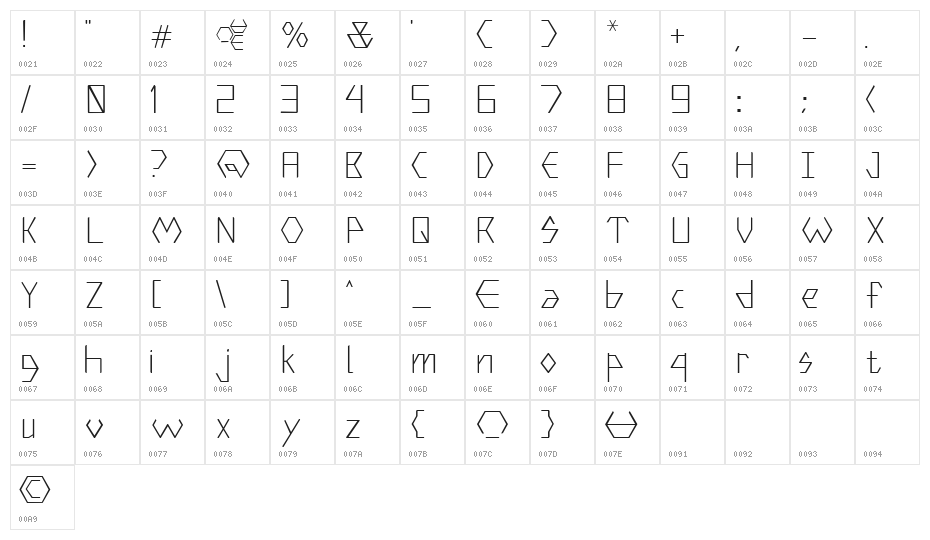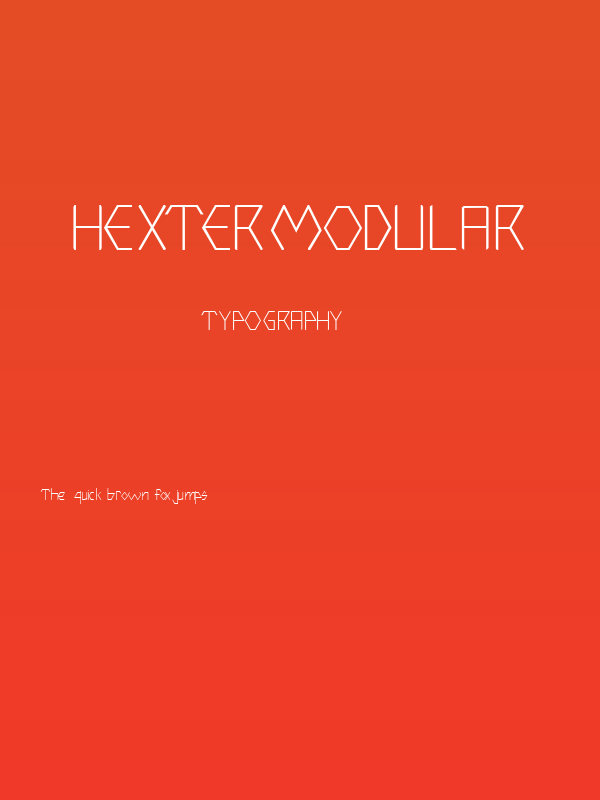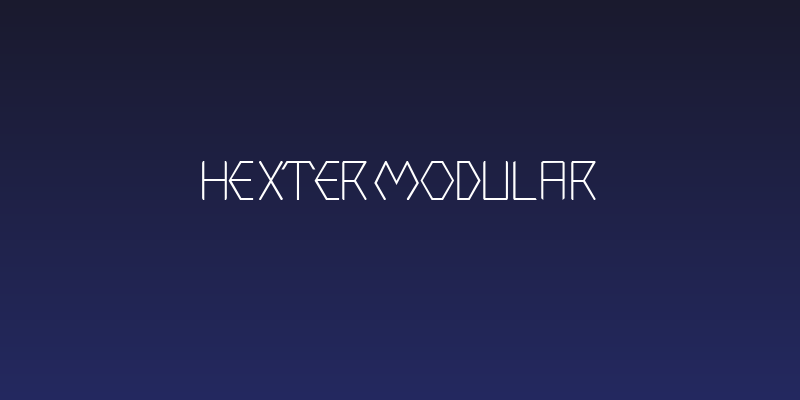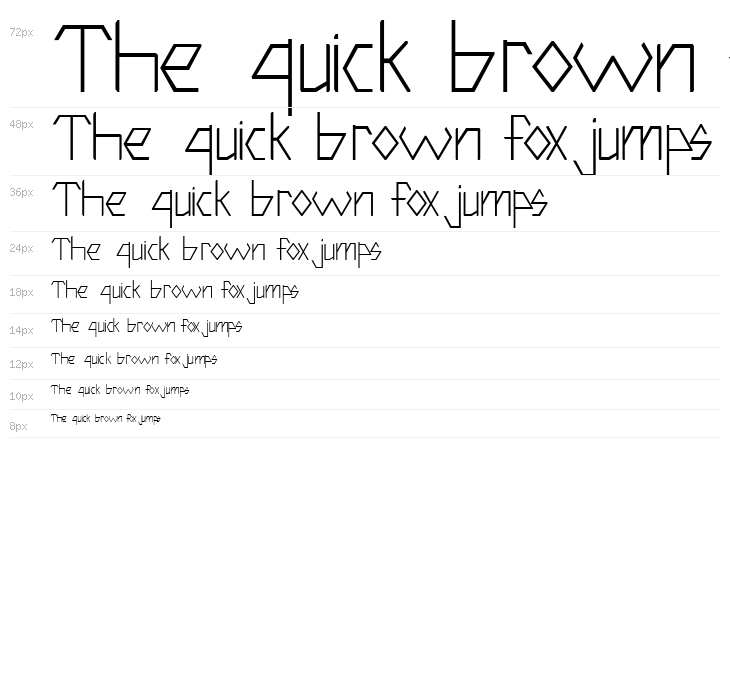
Hexter Modular Font
| Caso de uso | Logos, Headlines, Posters |
| Proyectos propuestos | Ideal for technology branding, sci-fi book covers, video game interfaces, and modern poster designs. |